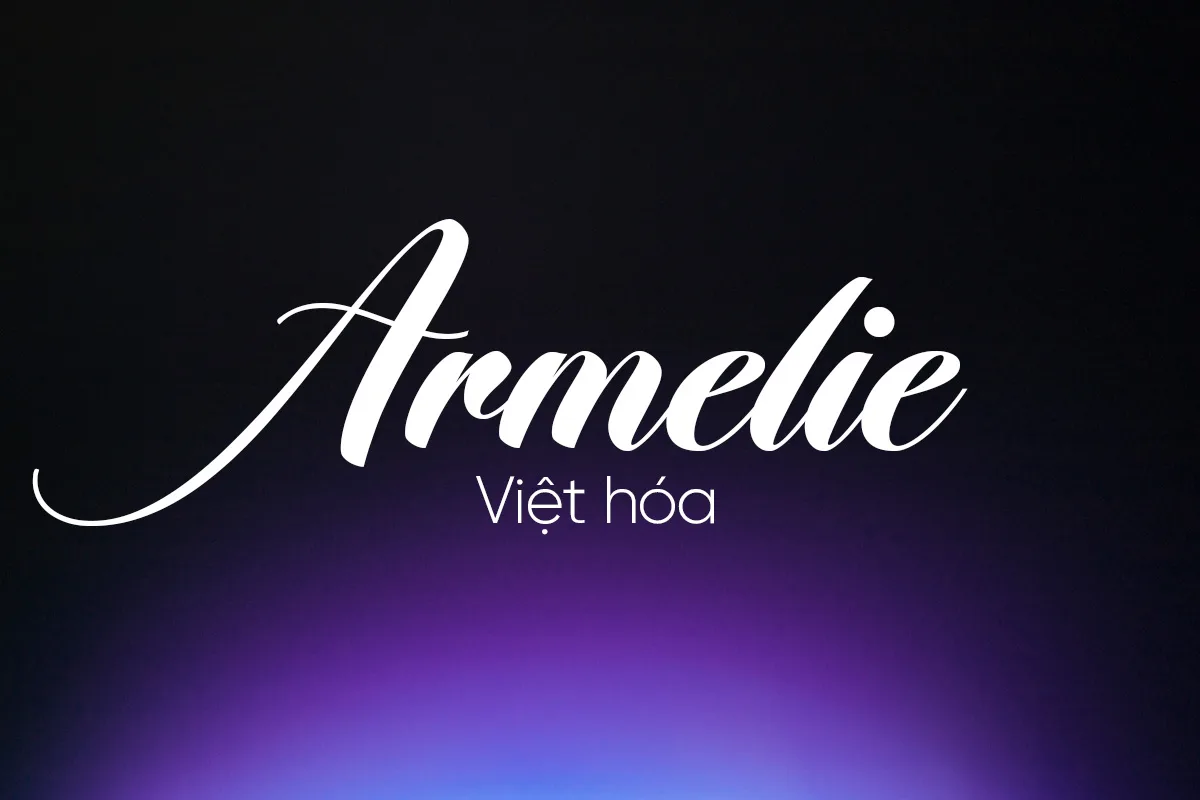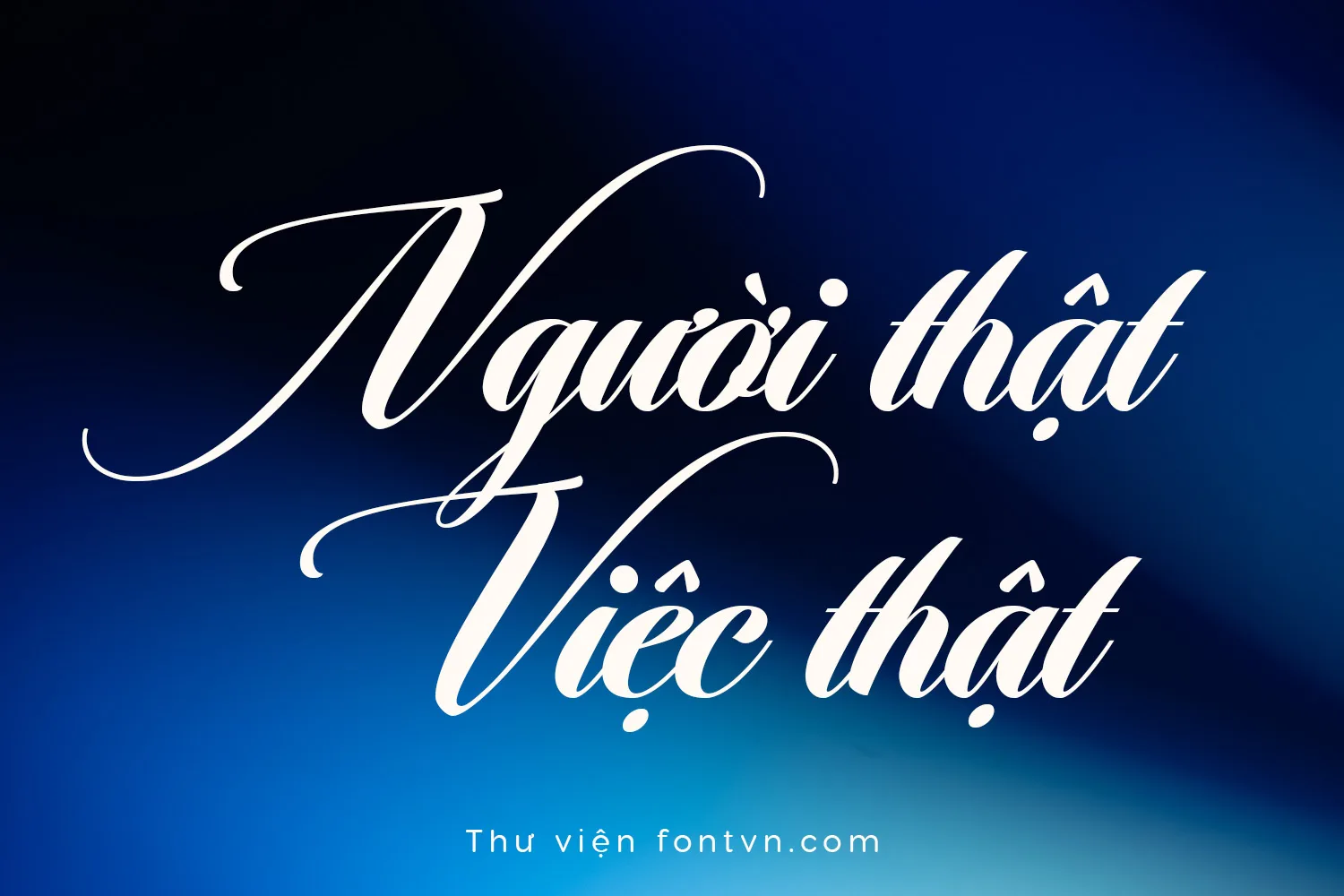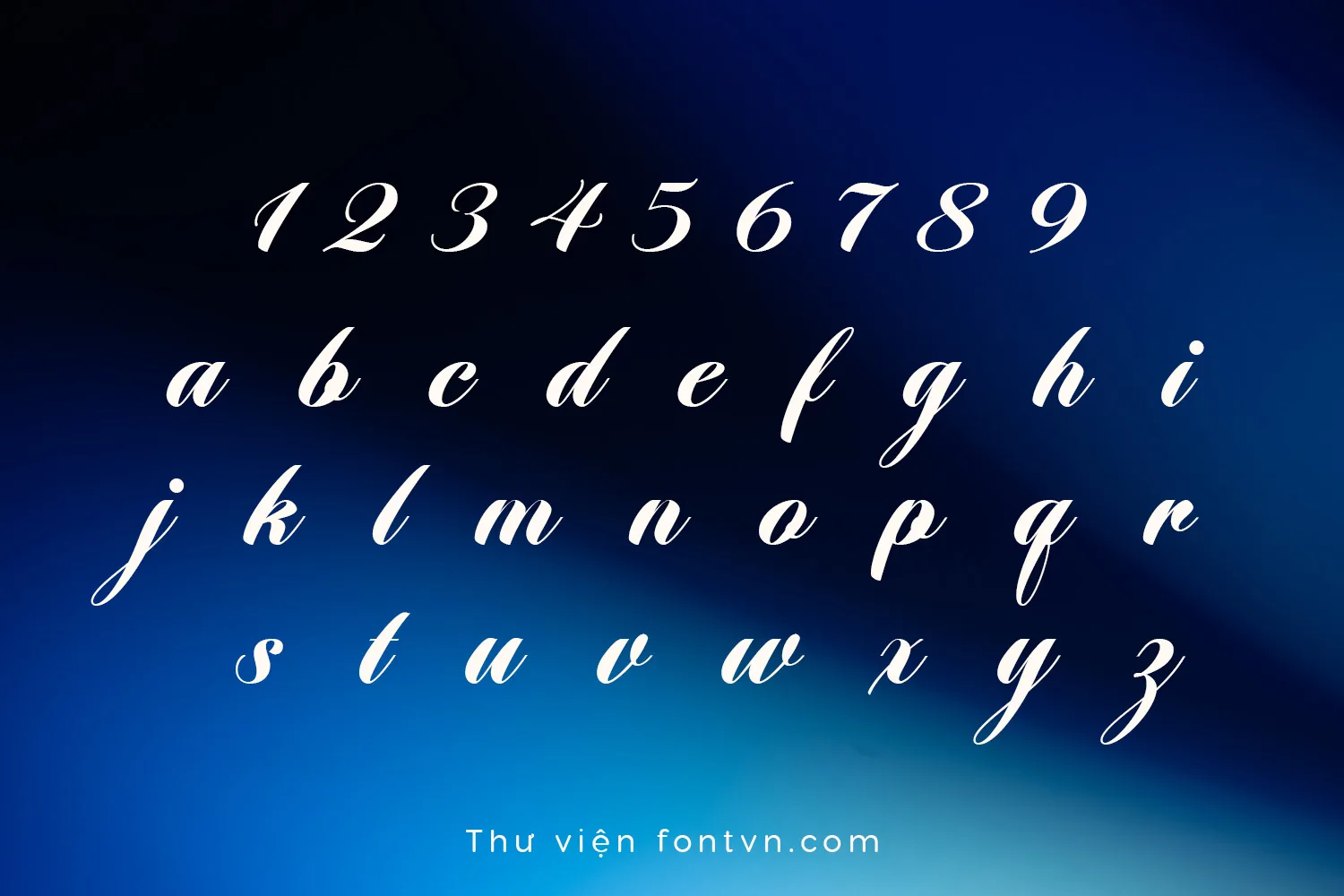
DVN Armelie Việt hóa – Font Script Thanh Lịch Đậm Chất Nghệ Thuật Cho Thiết Kế Cao Cấp
DVN Armelie là font chữ script mềm mại với những đường cong uyển chuyển và nét lượn tinh tế, mang đậm phong cách sang trọng và nữ tính. Các ký tự được thiết kế liền mạch, độ tương phản nét rõ ràng, tạo cảm giác bay bổng nhưng vẫn giữ được sự chỉn chu và chuyên nghiệp.
Phiên bản Việt hóa được tối ưu đầy đủ dấu tiếng Việt, đảm bảo hiển thị đẹp mắt và hài hòa trong mọi bố cục. DVN Armelie đặc biệt phù hợp cho thiết kế logo, branding mỹ phẩm – thời trang, thiệp cưới, quote nghệ thuật hoặc các ấn phẩm cần vẻ đẹp thanh lịch và cuốn hút.